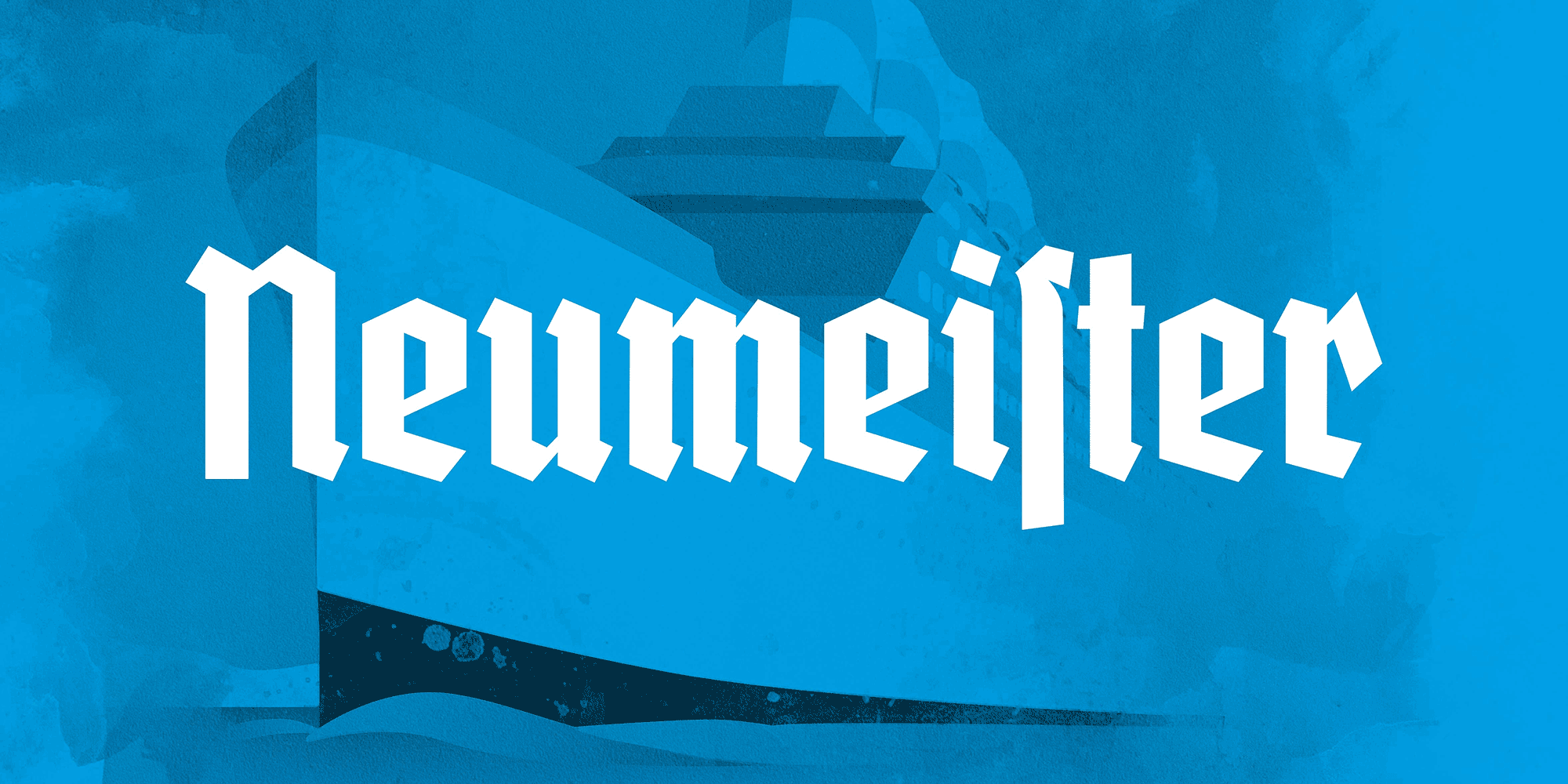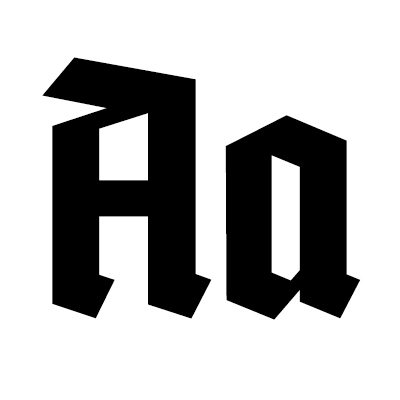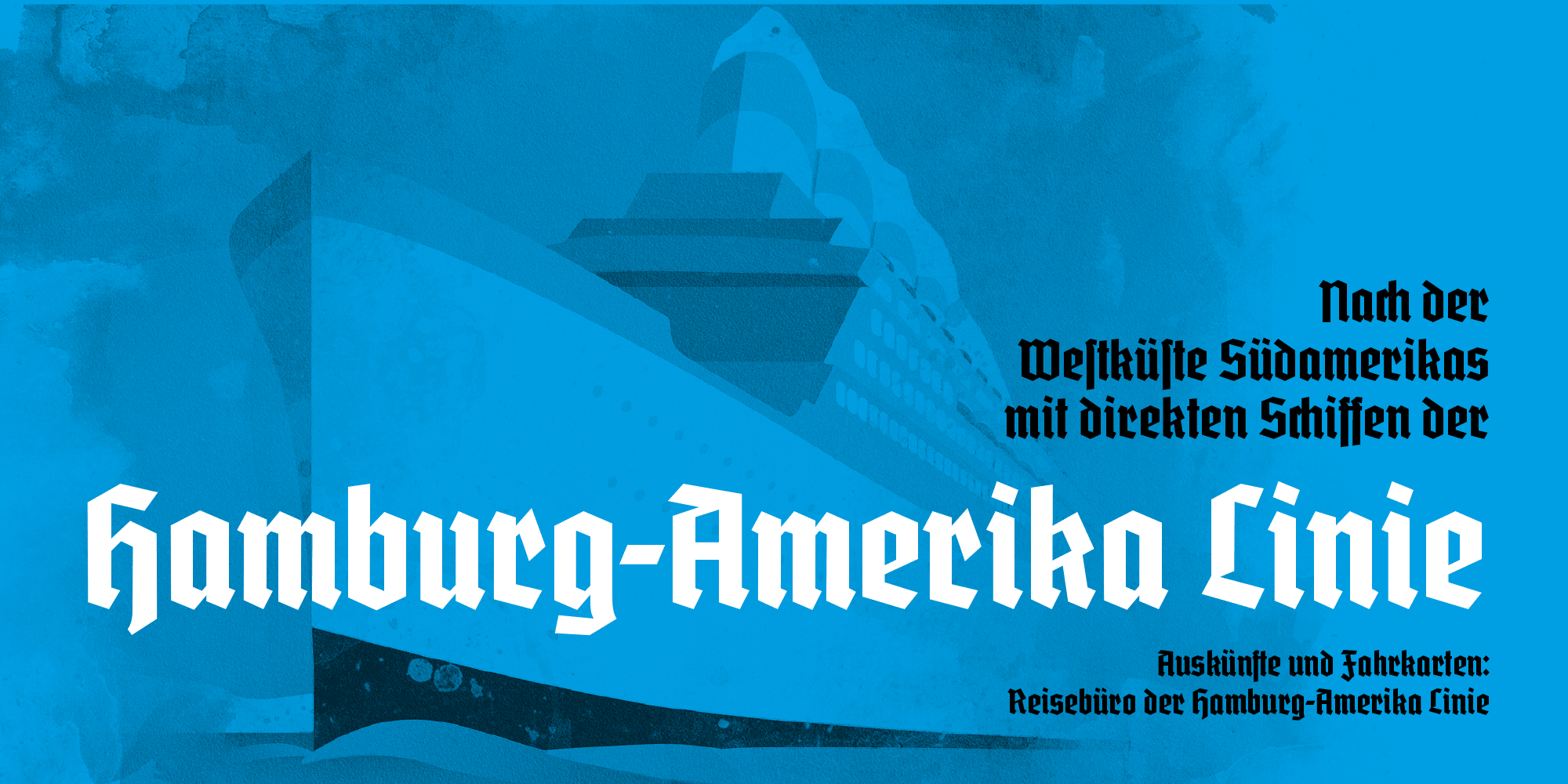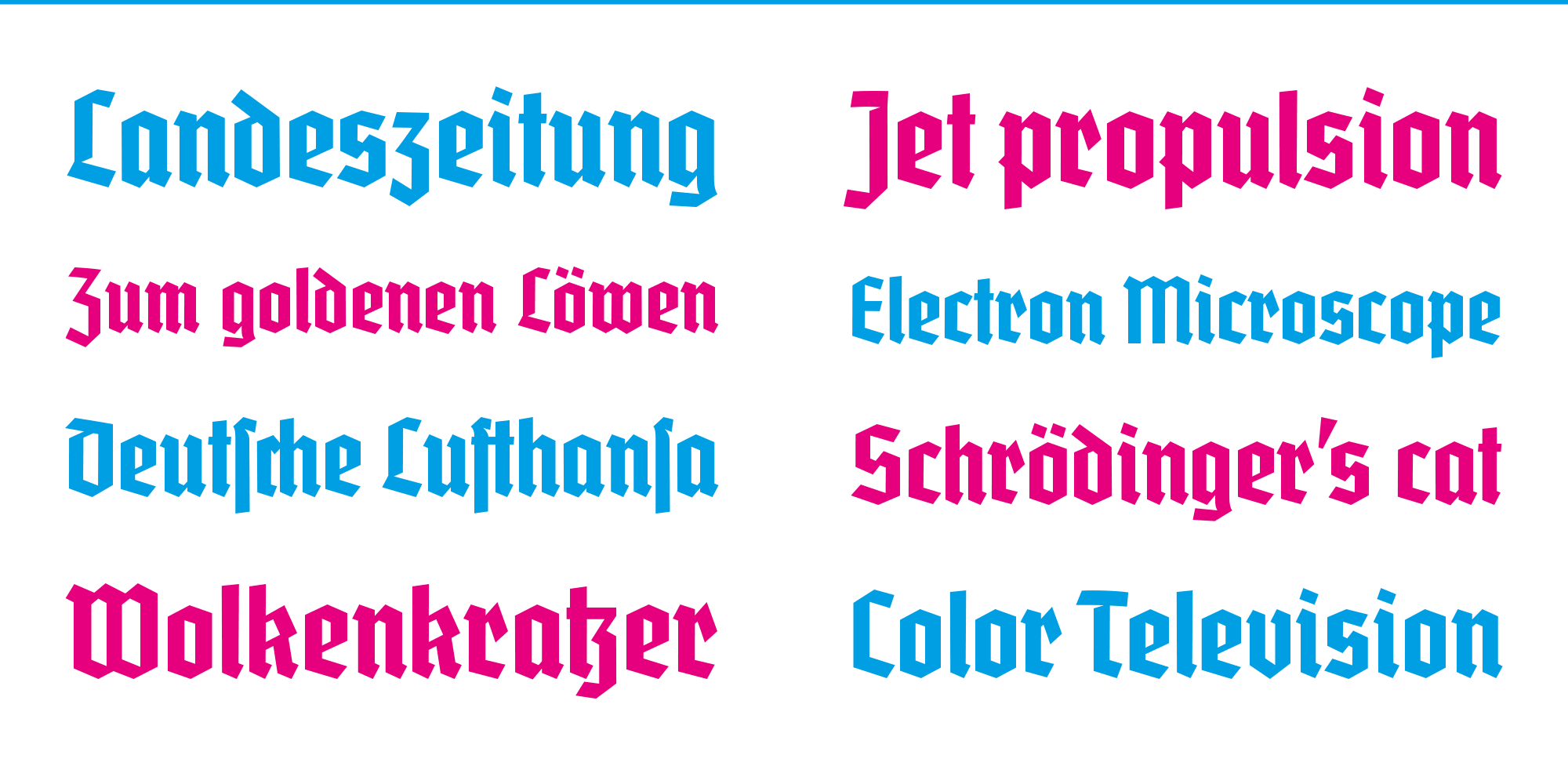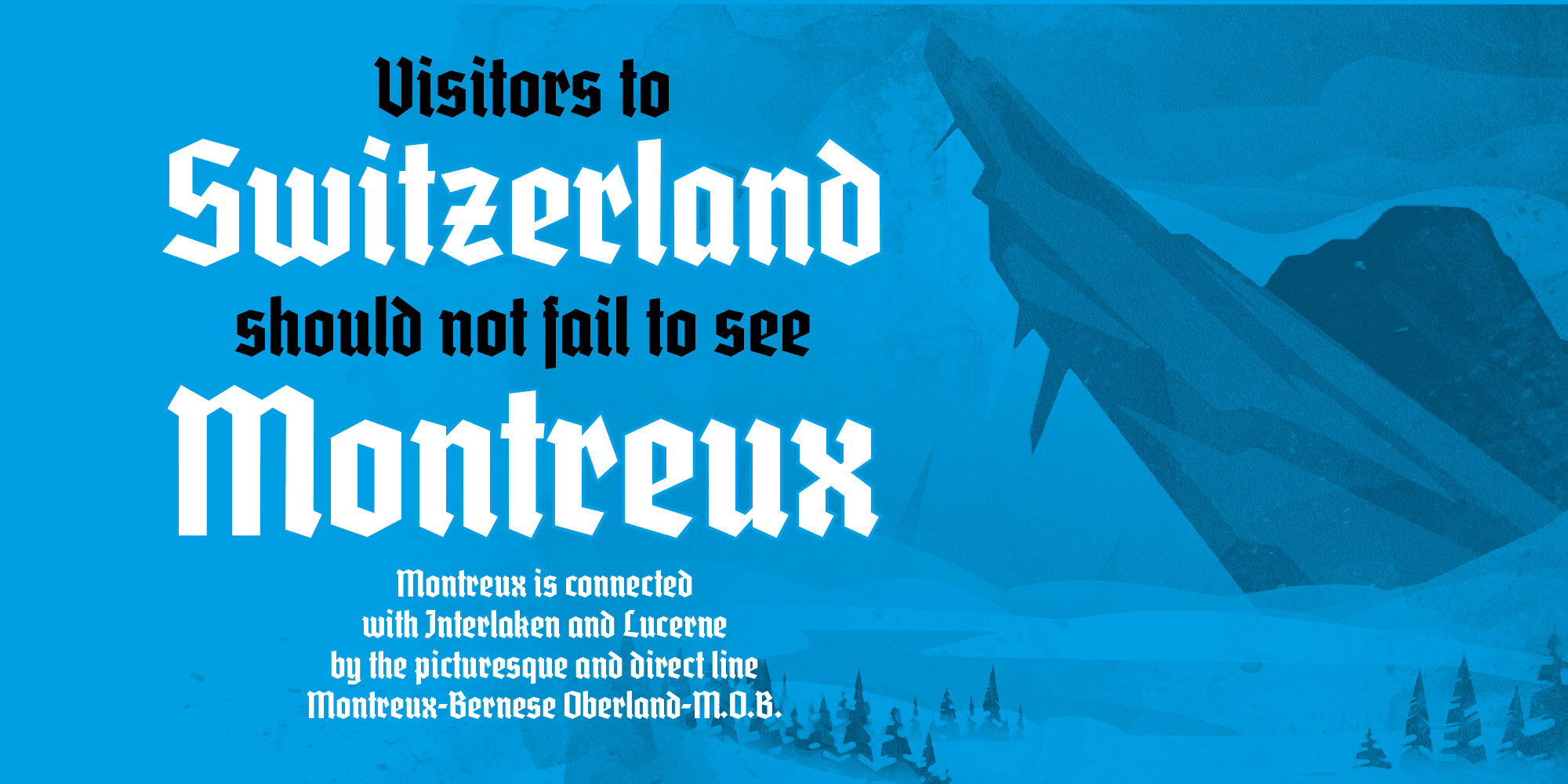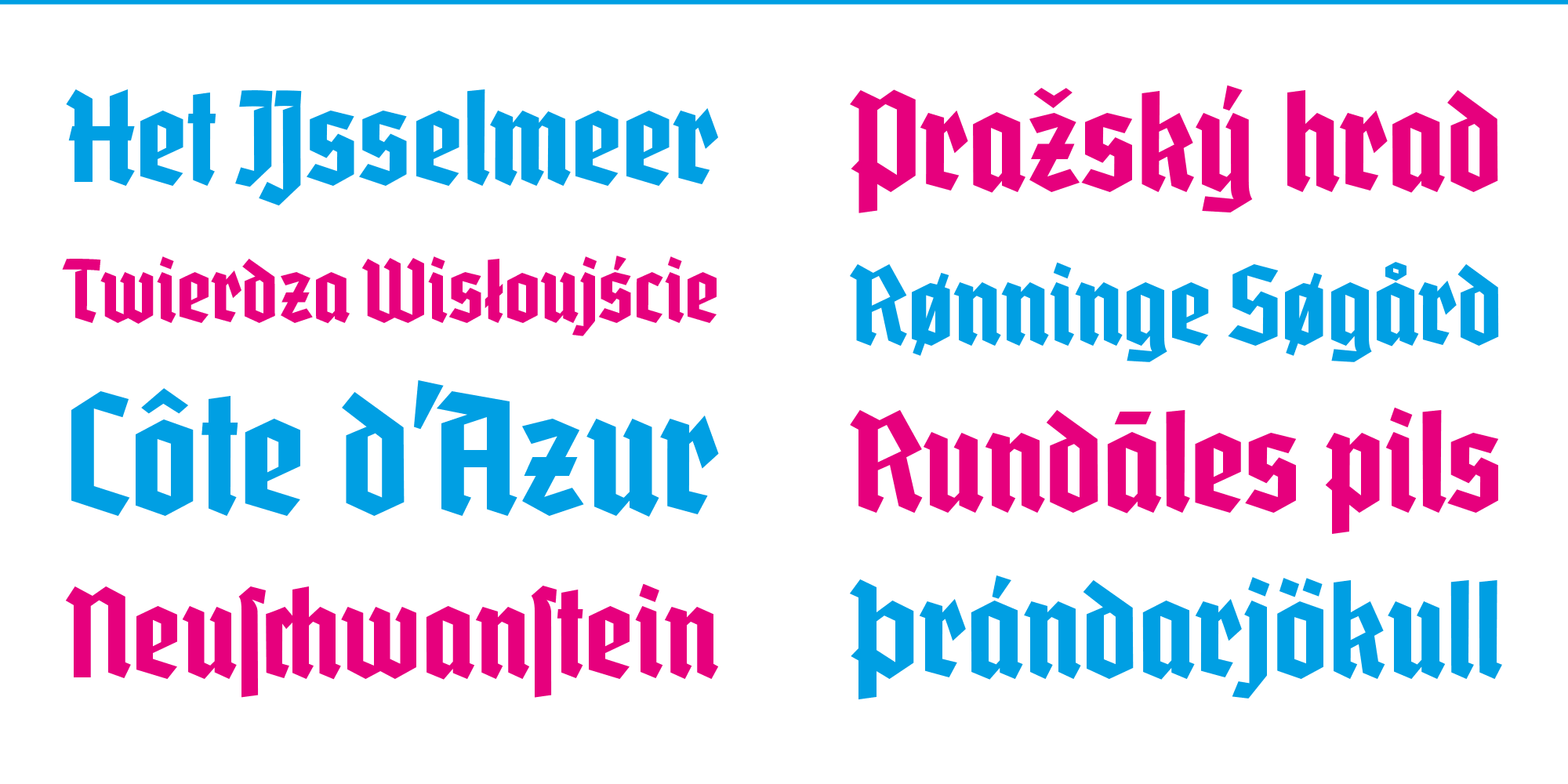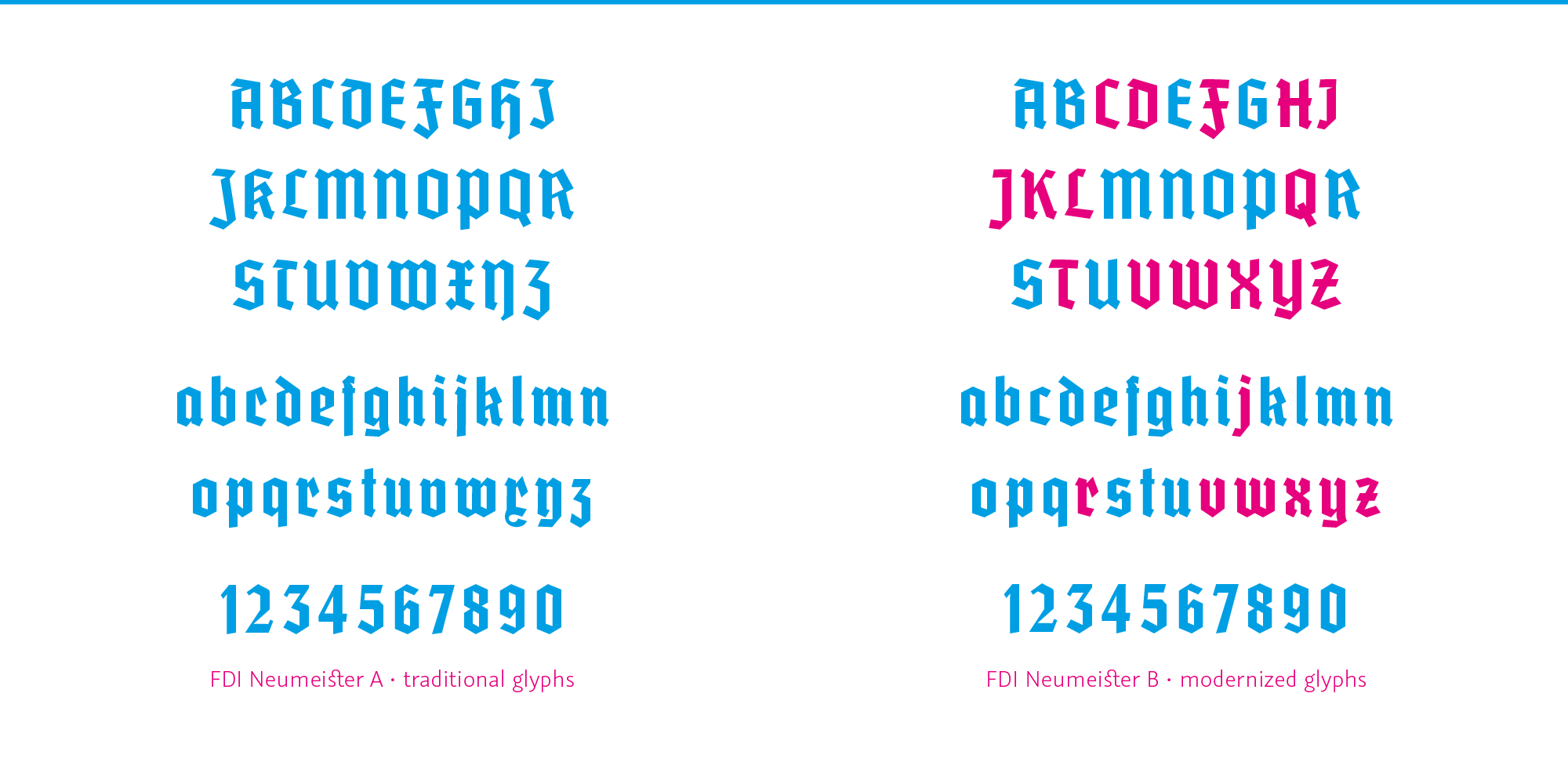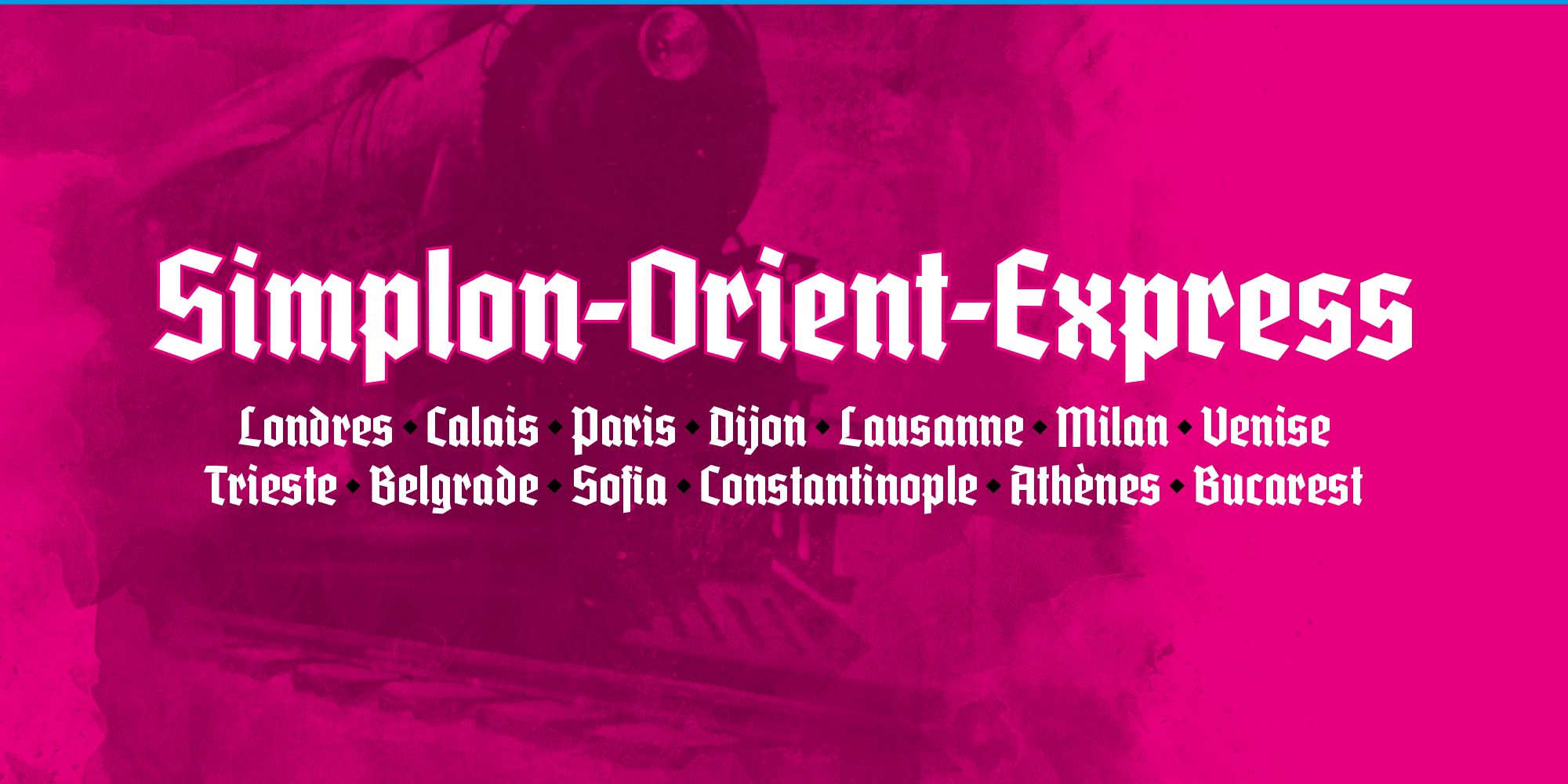
Eine umfangreich ausgebaute Digitalisierung der Deutschmeister schmalfett, veröffentlicht unter OFL-Lizenz nach einer Kickstarter-Kampagne. Version A enthält die ursprünglichen Glyphen, die mit den bedingten Ligaturen für traditionellen Fraktursatz eingesetzt werden können. Version B enthält modernisierte Glyphen-Varianten für eine bessere Lesbarkeit und eine internationale Anwendung.